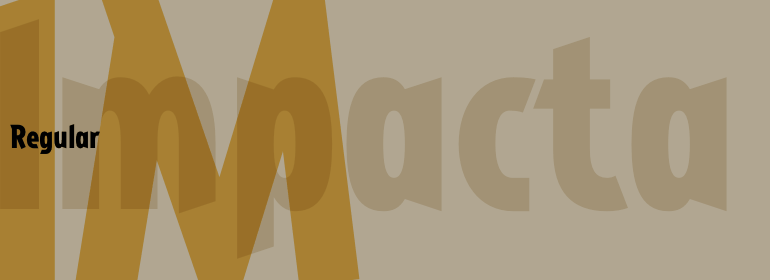
Impacta™
Linotype Impacta是TakeType字体库的一部分,该字体库收录了自1994年至1997年Linotype International Digital Type Design Contest的优胜者。荷兰艺术家Marc Lubbers设计了Impacta,笔画之间几乎没有对比度,确切的说,他是依靠倾斜的笔画赋予了字体个性。Impacta的大小尺寸均可用,其字形结构使平面设计多了一份现代感。
Linotype Impacta is part of the TakeType Library, which features the winners of Linotype's International Digital Type Design Contest from 1994 to 1997. Dutch artist Marc Lubbers designed Impacta with little contrast between strokes, rather, he depended on the slope of the strokes to give his font character. Impacta can be used in small or large point sizes and its constructed forms bring a modern feel to graphic design.